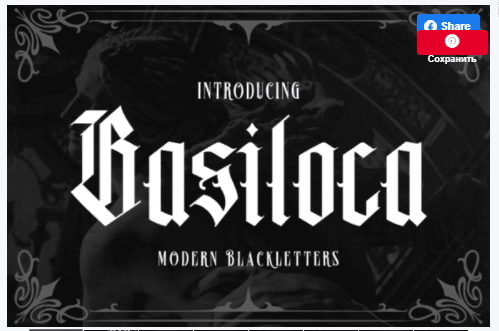
Basiloca Font
Basiloca - это очень подробный и напористый шрифт черного цвета. Этот оригинальный вид подойдет для самых разных творческих идей, от фирменных бланков и заголовков до канцелярских товаров.